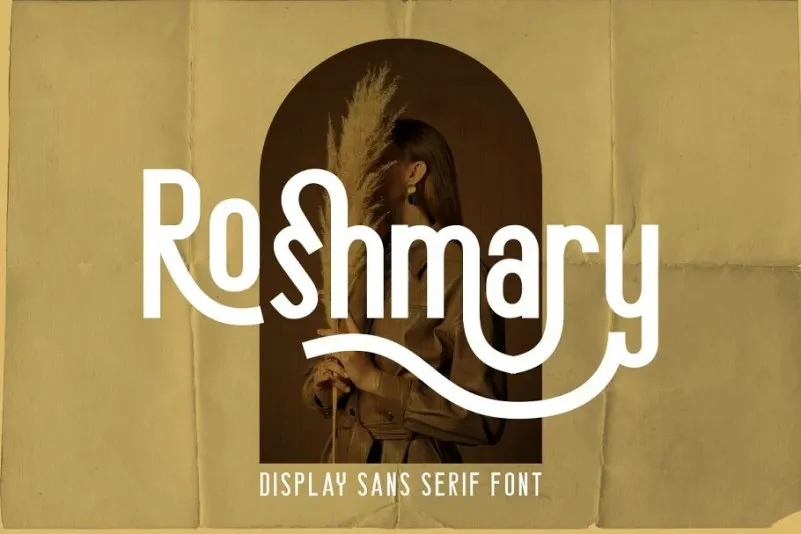
Roshmary Font – Fonte Grátis
Roshmary Font
A Roshmary é uma fonte sans serif que surgiu do talento criativo da 99designs, com um design limpo, elegante e sofisticado. Ela traz a essência de modernidade e simplicidade que o estilo sans serif representa, sendo perfeitamente adaptável para diversas aplicações visuais. Suas linhas são levemente afiadas e retas, projetadas para criar uma impressão forte e direta. O fato de ser uma fonte com alternativas de tipografia aberta oferece a vantagem de tornar a criação de letras muito mais variada e interessante. A Roshmary é perfeitamente adequada para aplicações que incluem logotipos, capas de produtos ou até mesmo cartões de aniversário, garantindo um acabamento impecável em qualquer projeto visual. Não hesite em experimentá-la; ela certamente encaixará perfeitamente com seu próximo design gráfico.